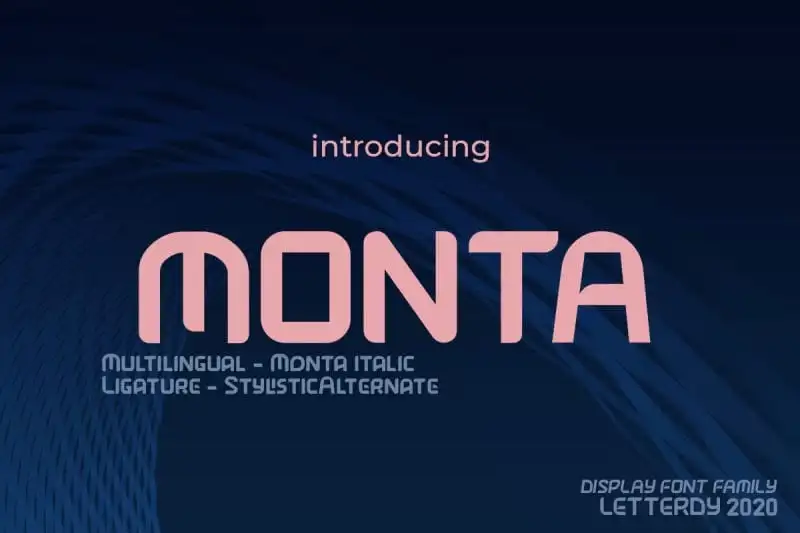
Monta Display Font
A Monta Display Font é uma nova face de tipo fresca e única, projetada com uma visão moderna que destaca seu uso incrível para branding e design impresso. Perfeita para títulos e cabeçalhos, esta fonte leva sua marca ainda mais longe no ambiente digital. Ela foi criada pelo Letterdy Studio e agora pode ser usada em diversos projetos de design gráfico. Com duas versões de estilo diferente – Monta Regular e Monta Italic -, a Monta Display é perfeita para qualquer projeto que exija um ar de sofisticação e modernidade. Quebre as barreiras tradicionais do tipo com a Monta Display, transformando suas ideias em realidade através de uma fonte que destaca sua personalidade única no mercado visual.